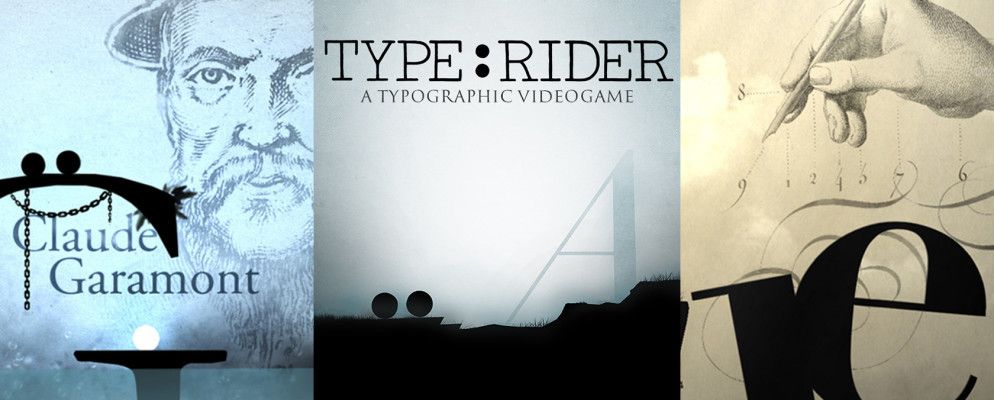
“我单击哪个选项卡可获得不同的字体样式?"乔布斯问,转身看一下他的团队。在推出Lisa之前,他们有很多工作要做,并且一名员工敢于说字体不是优先考虑的问题。乔布斯以险恶的目光当场开除他,大喊:“滚出去!"。
字体很重要。新乔布斯电影中的那个场景表明了这一点。 Google的Lato字体使PCPC.me如此令人愉悦地阅读。您能想象一台不能让您一键在Times New Roman和Arial之间切换的计算机吗?
Type:Rider是一款适用于iOS和Android的新游戏,希望庆祝版式的历史,而让您一路开心。有很多方法可以在线学习印刷术,但是玩游戏显然是最有趣的!
这是怎么回事?
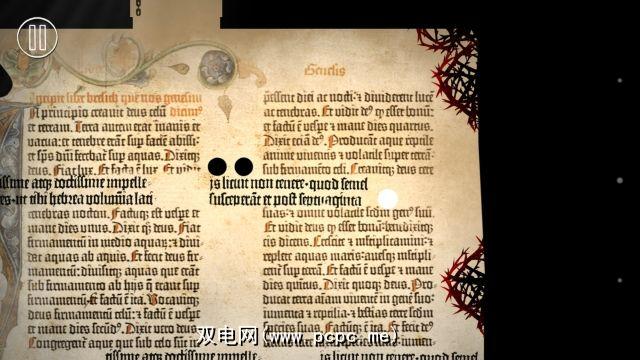
我喜欢Type:Rider的外观。使游戏看起来像您看到的一切都是剪影,除了背景。您扮演两个时期–好像两个轮子的顶部有一个看不见的越野车,但我喜欢将其视为不完整的椭圆。我称之为“椭圆车"。
基于物理学的游戏是通过使用屏幕上的按钮倾斜智能手机或使用“直观控件"来控制的,其中您可以点击屏幕的左侧或右侧朝那个方向移动,按住一个并点击另一个即可跳跃。直观的控件不辜负它们的名字,并且是我玩游戏的首选方式。
在每个级别中,您都必须四处移动车来收集散落的字母。跳跃,游泳,避免尖刺-这是平台游戏的常规收费,但执行效果非常好。 Type:Rider从来没有感觉过容易,但它也从来没有像现在这样具有挑战性,您可以放弃它。
了解字体
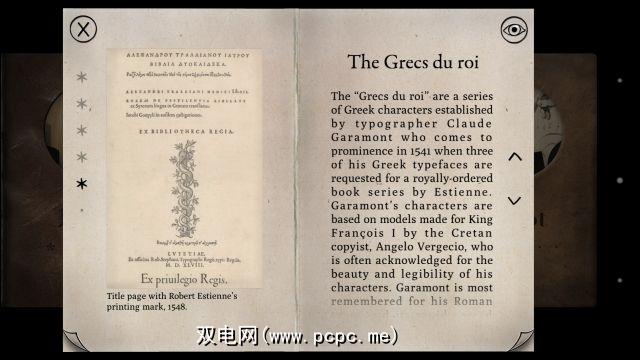
关卡本身专用于单个字体。因此,哥特式字体具有所有的迷你级别,其次是Garamond及其拼图,依此类推。字体被编织到关卡设计中,成为您的越野车经过或出现在背景场景中的平台。
完成每个微型关卡将解锁一本书中的一章,向您介绍有关字体的更多信息历史。解锁每本字体书中的每一章,以了解所有需要了解的知识。实际上,这很酷,令我惊讶的是我停下来阅读每一章,而不仅仅是继续学习下一章。
Type:Rider擅长的是在游戏中加入版式,然后简短介绍关于它的教育性话语,其次是更多的游戏性和教育性。结合您在演奏时随处都能看到字体的事实以及在关卡末尾必须消化的少量信息这一事实,可以使您想进一步了解字体。两者是无缝连接的,这与许多教育游戏不同,后者将游戏玩法作为与分散知识的薄弱环节。
但这值得吗?